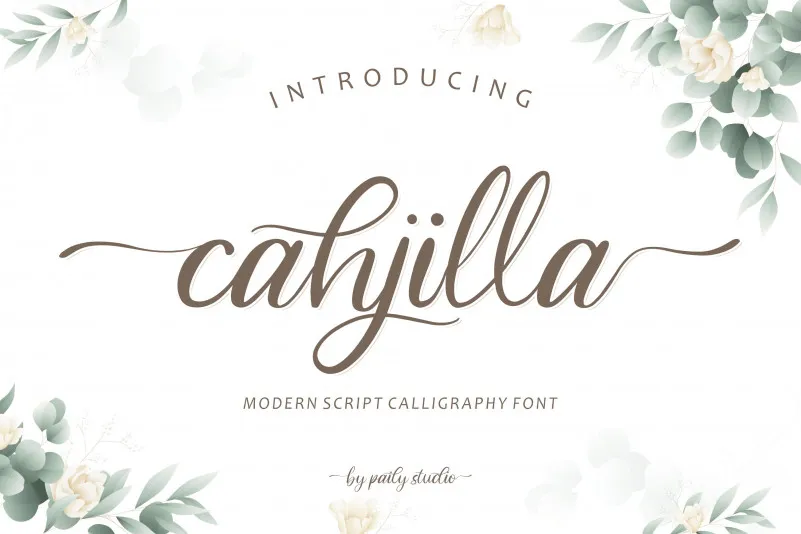
Cahjilla Font – Download Grátis
A Cjahilla é uma fonte de caligrafia moderna perfeitamente adequada para diversos aplicativos gráficos. Seu design sofisticado e elegante pode ser usado em um vasto leque de projetos, incluindo design de casamentos, criação de marcas, logotipos, postais, cartões de nome, convites e publicações no Instagram ou Facebook, entre outros. Essa fonte é ideal para quem procura uma aparição elegante que ainda respeita o seu estilo personalizado. A Cjahilla é mais do que um recurso gráfico: ela transforma qualquer projeto em algo impecável. Para projetos que exigem detalhes exatos, a Cjahilla não se mostra insuperável. Ela oferece uma variedade de opções para diferentes níveis de personalização, permitindo que você ajuste sua aparência e tamanho conforme o projeto requer. Ideal tanto para iniciantes quanto para designers mais experientes, essa fonte é um ótimo investimento para qualquer estúdio gráfico, oferecendo qualidade de design impecável em toda a sua extensão de uso.